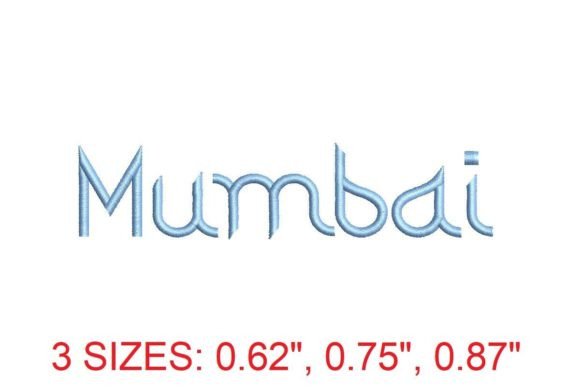
Mumbai Embroidery Font
Mumbai Embroidery Font — це високоякісний набір літер, спеціально розроблений для машинної вишивки з використанням формату PES. Завдяки своєму унікальному індійському естетичному підходу, шрифт поєднує традиційні орнаментальні мотиви Мумбаї з сучасною технікою цифрової вишивки. Кожна літера є не просто символом, а самостійним художнім елементом: вона має чітко прораховані стежки, оптимізовані для стабільного проходження нитки та мінімального сковзання тканини, що робить його ідеальним для професійних вишивальників та дизайнерів, які шукать щось більше за звичайні шрифти.
Якість збірки та технічні деталі
Для кого найкраще підходить цей продукт?
Цей шрифт ідеально підійде професійним вишивальникам, які працюють з брендованими продуктами, особливо в сегменті моди, гостинності та подарункової продукції з індійським або глобальним культурним акцентом. Також він стане знахідкою для дизайнерів вишивки, які створюють кастомні шаблони для мерчандайзингу, подій (весілля, корпоративні заходи) або етнічних колекцій. Не рекомендований для початківців без базового розуміння PES-структури або для використання на дуже тонких/еластичних тканинах без додаткової стабілізації.
Перед вишивкою завжди виконуйте test stitch на тій самій тканині та з тими самими нитками, що будуть використані у фінальному продукті — Mumbai Font має щільне заповнення, і на деяких матеріалах може знадобитися додаткова підкладка або зменшення щільності стежки в програмі редагування (напр., Wilcom E4/EPS).
Як це порівнюється з конкурентами
На відміну від загальних шрифтів типу 'Taj Mahal Script' або 'Bollywood Bold', Mumbai Embroidery Font має повну підтримку всіх знаків пунктуації та цифрових значень у кожному розмірі, а не лише літер. Порівняно з платними аналогами від OESD або Amazing Designs, він пропонує кращу оптимізацію для середньої швидкості вишивки (600–800 стежок/хв), меншу кількість перерв у нитці та більш природні контури літер, що зберігають етнічну естетику навіть у мініатюрних розмірах (1.5″). Однак він не має вбудованих варіантів для вишивки з металевими нитками — це вимагає ручної доопрацювання.